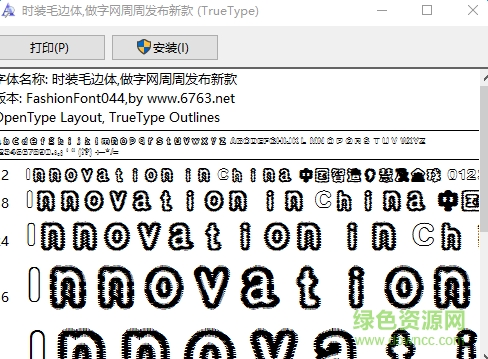
時(shí)裝毛邊體是時(shí)裝字庫(kù)中的一款很有特色的藝術(shù)字體,這款字體寫出來的效果就像它的名字所說那樣是帶有毛邊的,是不是很有趣呢,喜歡的朋友就快來綠色資源網(wǎng)下載吧。
時(shí)裝毛邊體是一款很不錯(cuò)的電腦字體,有著藝術(shù)風(fēng)格,所以用于藝術(shù)設(shè)計(jì)、廣告設(shè)計(jì)都是很不錯(cuò)的,歡迎大家來綠色資源網(wǎng)下載。